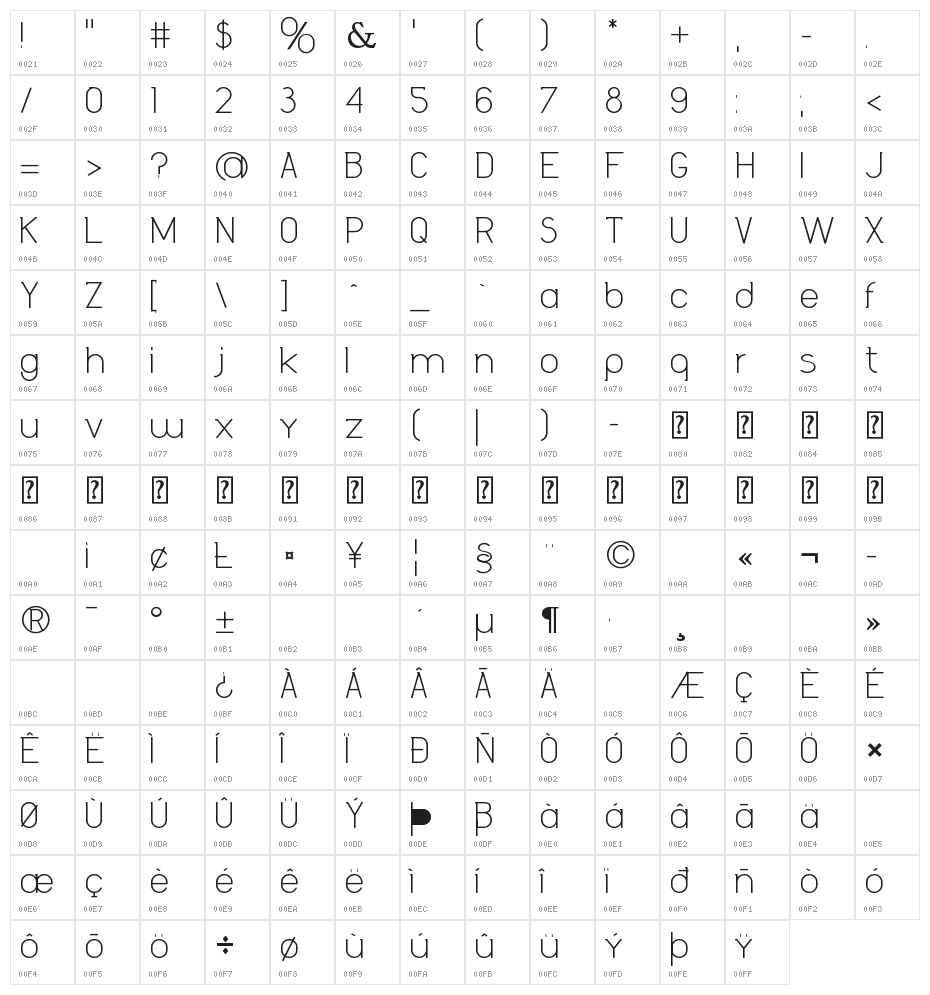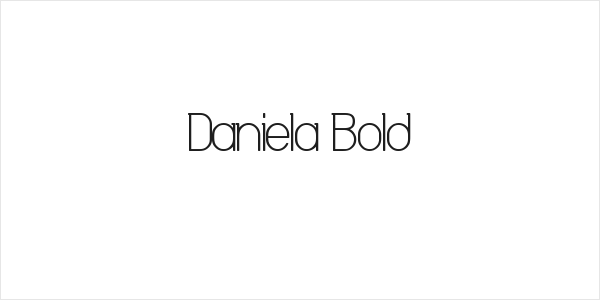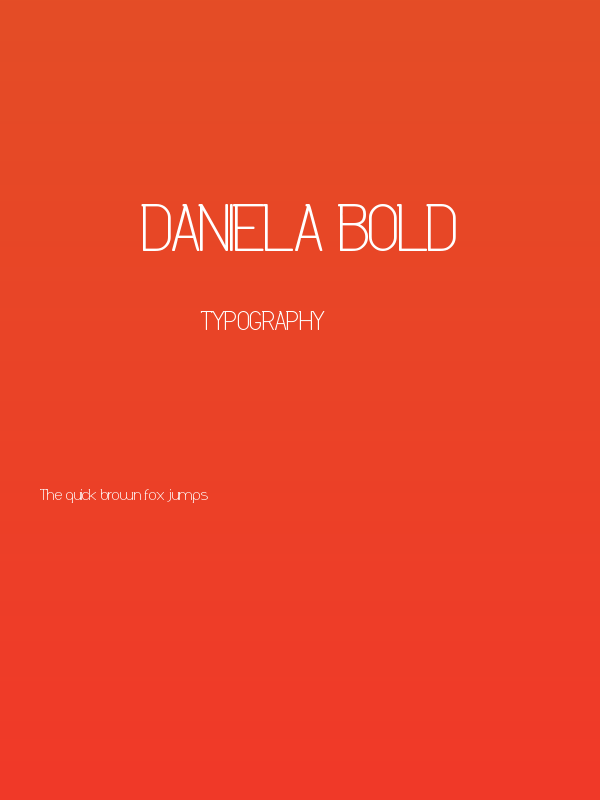
Daniela Bold Font
| Anwendungsfall | Headlines, Logos, Branding |
| Vorgeschlagene Projekte | Ideal for branding, advertising, web design, and editorial projects that require a modern and clean look. |